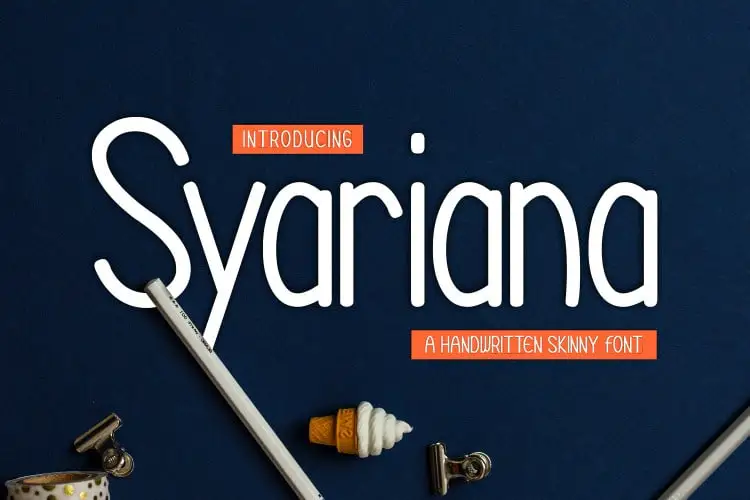
Syariana Sans Serif Font – Download Grátis
A Syariana Sans Serif Font é uma opção envolventemente atraente para qualquer projeto visual que busque transmitir simplicidade e elegância através de seu design clean, mas com um toque carinhoso e humano. Seu estilo natural e único faz dela perfeitamente adequada para uma ampla gama de designs. A única limitação é a imaginação do criador. Com esta fonte, você pode explorar sua criatividade sem fim ao criar design digital que vai do logotipo e identidade visual até o layout de revistas ou qualquer outro uso imaginável. Seja em uma apresentação de PowerPoint criativa para um webinar ou um infográfico impactante na web, Syariana Sans Serif é a escolha ideal para levar seu projeto ao próximo nível.